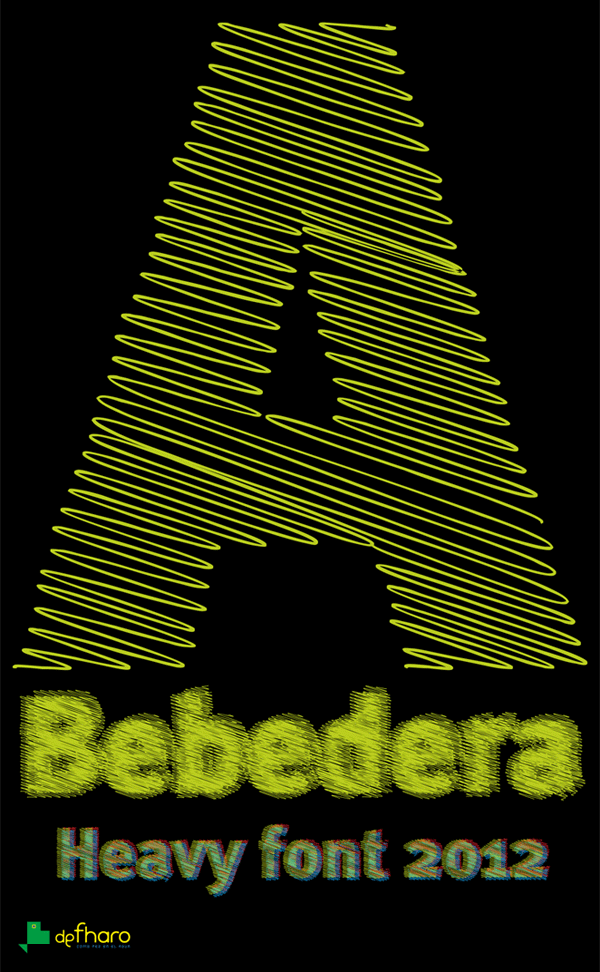
Font name: | A Bebedera |
A Bebedera: esta frase portuguesa viene a significar "la borrachera", le he puesto dicho nombre por la cantidad de curvas que tiene cada glifo, el vaivén del borracho!! y el mareo que me he cogido yo, también, como homenaje a Brasil, donde viví y aprendí tanto. Es una tipografía Heavy y dispone de todos los acentos del latin. Gratis para uso personal. https://defharo.com/fonts/descargar-fuentes-gratis/ |